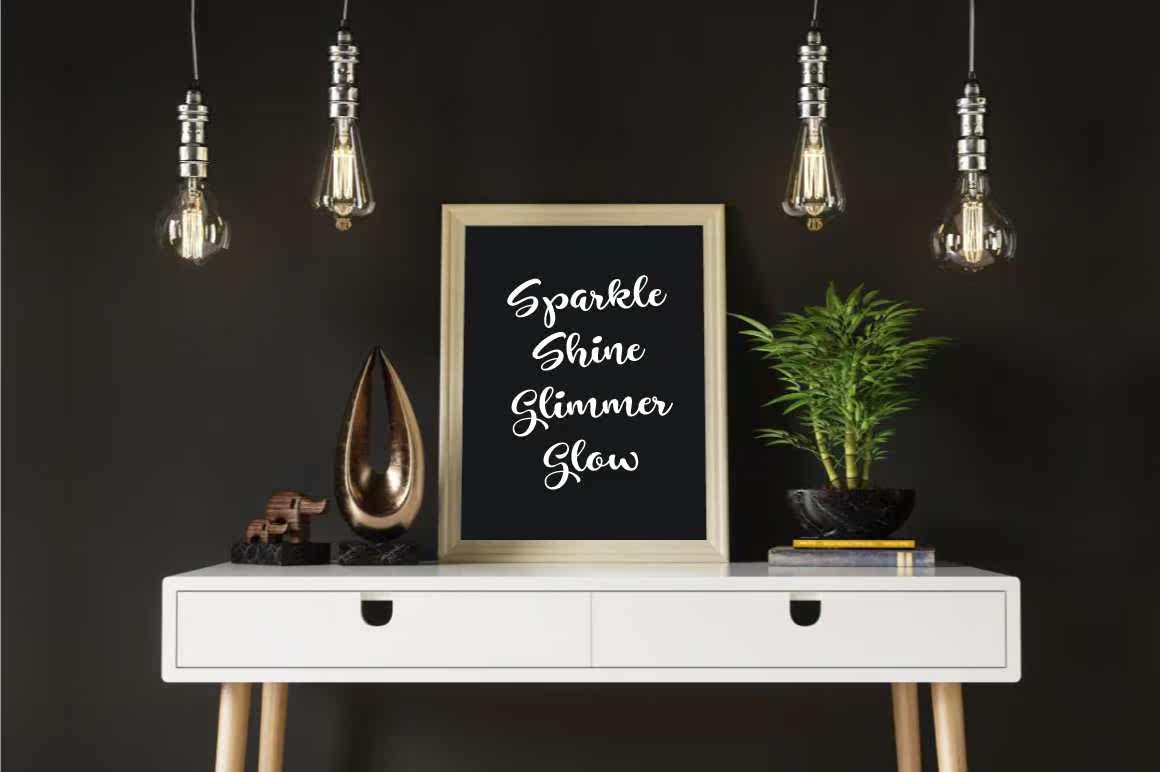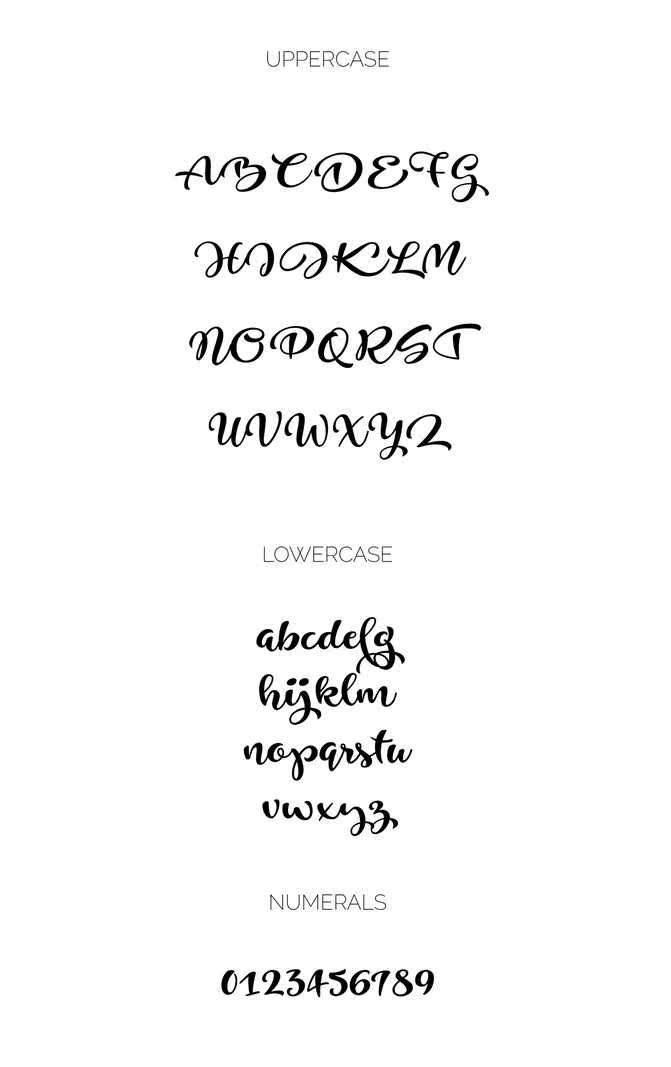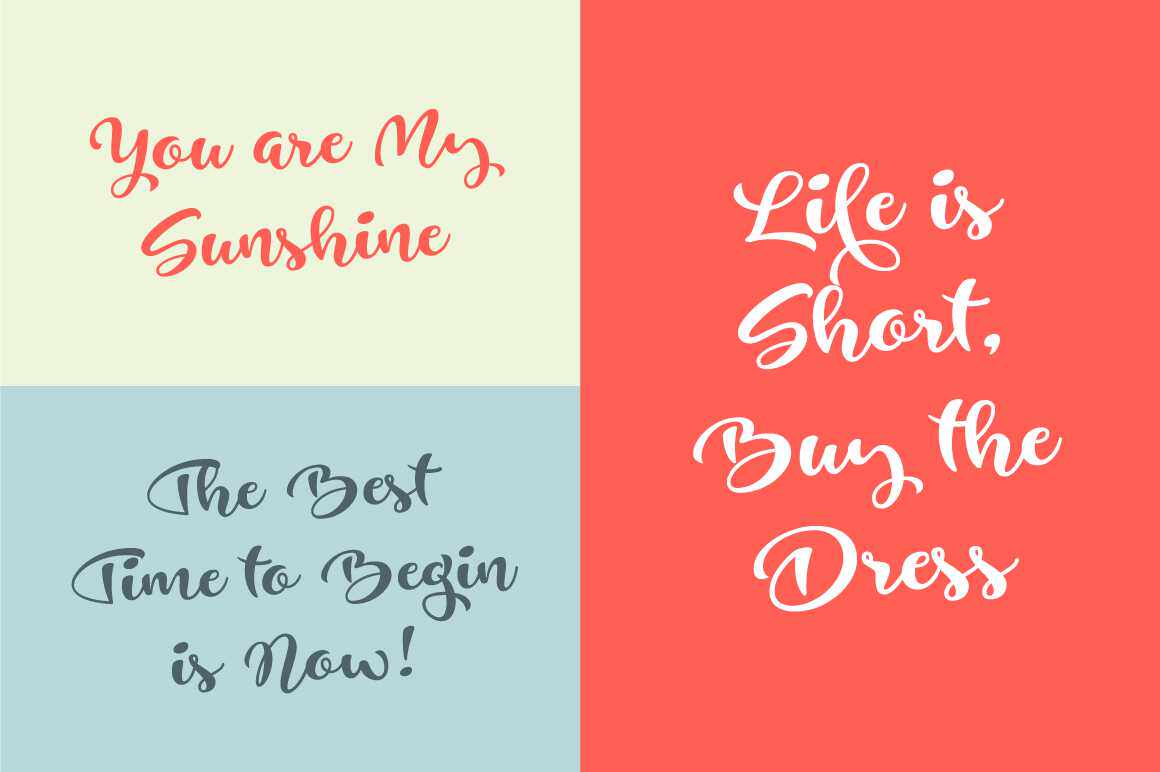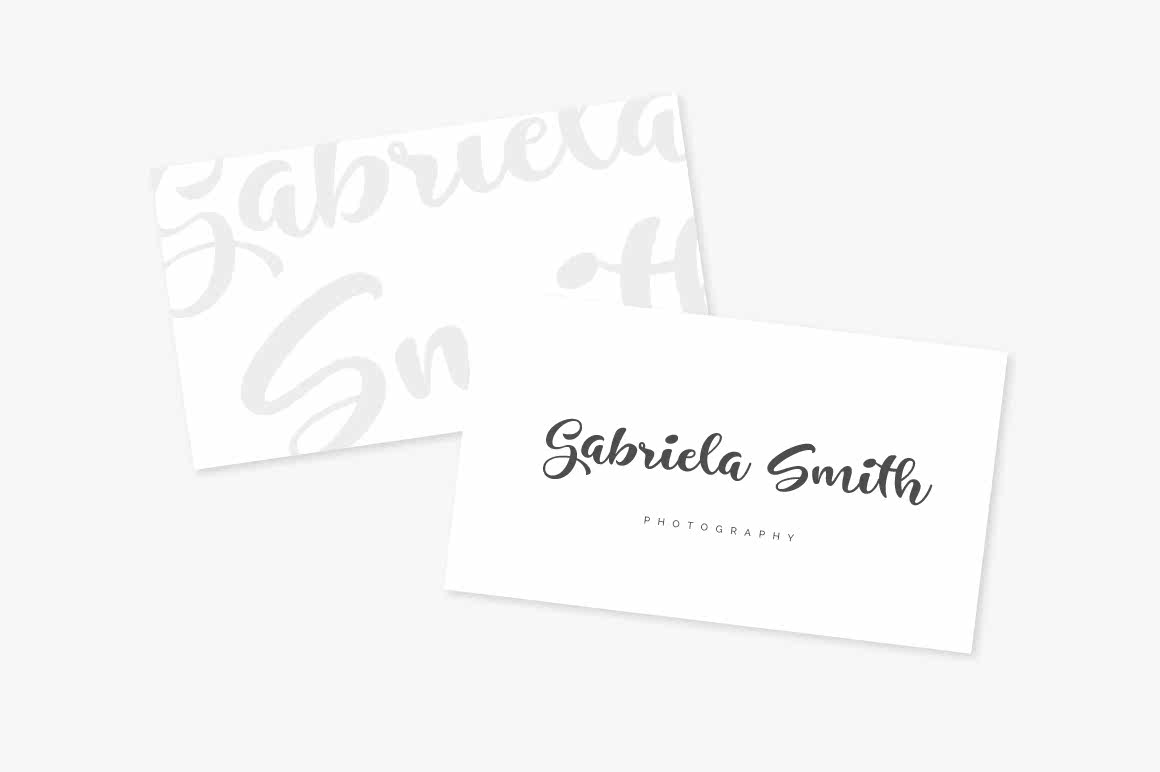
只有Beisaplayfullbrushscript.PerfectFortiles、Headings和Logotypes用于日志、产品和生活方式图像(如Equal和Stuff)。只有Beisaplayfullbrushscript.PerfectFortiles、Headings和Logotypes用于日志、产品和生活方式图像(如Equal和Stuff)。